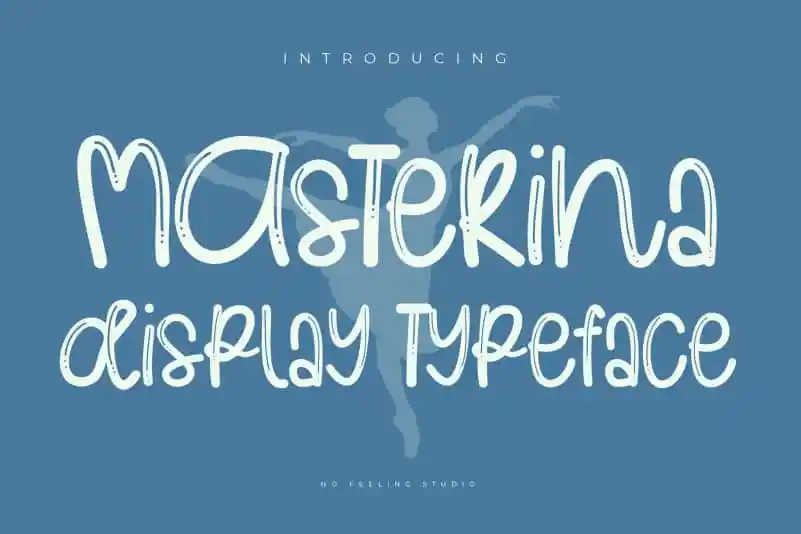
Masterina Brush Font – Fonte Grátis
Masterina Brush Font
A Masterina Brush Font é uma deliciosa escolha para quem procura algo único e alegre no seu projeto visual. Esta fonte foi criada através da mão do designer, resultando num estilo de traçado leve que se ajusta perfeitamente a muitos tipos de design gráfico. Ela é especialmente apropriada para trabalhos que precisam de letras manuscritas personalizadas ou que buscam um toque emotivo em seu projeto visual. Com sua natureza delicada e única, essa fonte encaixa-se bem em cartões de aniversário, calendários de scrapbooking ou até mesmo no design de logotipos. Sua versatilidade faz dela uma excelente adição para qualquer designer que procura um charme único em seu trabalho.